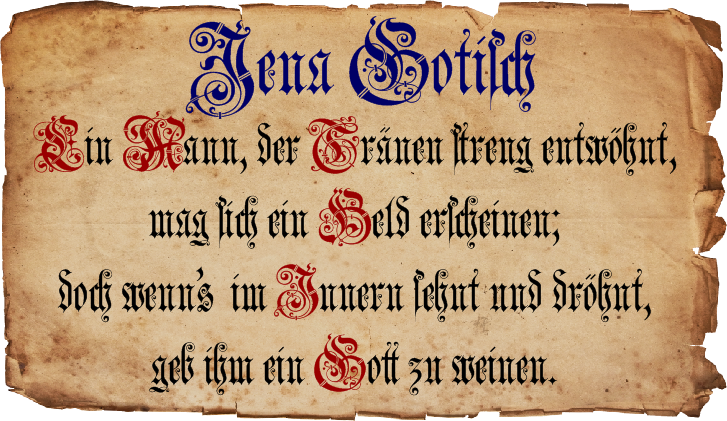
Zierelemente Renaissance
Ich habe mit großer Freude gelesen, dass die EB Garamond auch einen Font mit Initialen besitzt. Bei genauerem Hinsehen stellte sich leider heraus, dass es nur eine Handvoll Buchstaben sind, von denen auch nur zwei (A und T) wirklich gezeichnet sind, die anderen sind abgepaust. Das A gefällt mir allerdings sehr, dummerweise brauche ich ein K.
Ich habe Myfonts nach Alternativen durchsucht und auch die Suchmaschine mit Stichwörtern Renaissance / Initial etc. gefüttert – ohne Erfolg. Entweder passt es stilistisch nicht, oder die Buchstaben sind durch die Illustrator-Autotrace-Funktion gejagt worden und nicht sehr attraktiv. Kennt jemand von euch noch Orte, wo sich eine Suche lohnen würde? So sieht das A der EB Garamond aus:
Dieser Stil würde auch insofern hervorragend passen, da er auf einer Bibelausgabe basiert, die 1564 bei Jean de Tournes in Lyon gedruckt wurde. Das private typografische Experiment, an dem ich gerade arbeite, hat zufälligerweise historische Anleihen bei eben jenem Drucker aus Lyon genommen. Und das bringt mich zu einer zweiten Frage: Tournes Drucke sind mit vielen Zierelementen versehen, die von Bernard Salomon stammen. Eines dieser Elemente würde ich gern benutzen:
Es liegt mir ein Scan in leidlicher Auflösung vor; leider reicht es nicht, diesen als Bild oder als (Autotrace-)Vektor zu verwenden – das Ergebnis sieht nicht besonders gut aus. Man müsste das Ganze wohl sauber neu vektorisieren (und dabei Einzelheiten anpassen). Nun bin ich zwar nicht ganz ahnungslos in Sachen Illustrator-Zeichenwerkzeuge, aber das ist mir dann doch ein bisschen zu kompliziert. Die Frage ist, wer eine solche Vektorisierung übernehmen könnte und was das kosten würde?
Selbst das beste Autotrace ist bei solchen Sachen ja zumeist übelst.
Was die Schnörkelei anbelangt erinnert mich das an die ja auch der nach einem einen Beitrag hier entstandene Schrift:
Zugegeben, das liegt zeitlich deutlich später. Aber wenn es zeitlich Luft hat, und nicht gleich morgen fertig sein muss, beschaff mir doch mal einen Satz ordentlicher (hinreichender) Scans von den Initialen. So was interessiert mich schon sehr, da mal einen ordentlichen Initialen-Satz zu bauen, vielleiche auch noch so ein paar reine Grafikelemente, die ja damals auch gesetzt wurden, passend dazu auf die Gemeinen gelegt.
Danke, catfonts, für die Antwort. Was die Initialen angeht: Eine Ausgabe der besagten Bibel steht bei mir um die Ecke in Gotha, vielleicht kann ich bei Gelegenheit mal vorbeischauen und auf unbürokratische (und preiswerte) Art Fotos machen. Das Problem in Bezug auf mein konkretes Projekt: Die französische Bibelübersetzung hat offenbar kein Kapitel, das mit dem Buchstaben K beginnt (auf den es mir gerade ankommt); für diesen Initialbuchstaben gäbe es also, wenn ich nichts übersehen habe, keine Entsprechung. Aber lohnend scheint mir das Projekt trotzdem: Die Arbeiten von Salomon finde ich wunderschön.
Kein K? ... Nun gut, wenn man sich da eingeschnörkelt hat, muss man halt das K passend erfinden. Das Poblm hatte ich bei der Jena ja auch, das da ein Buchstbe fehlte. Da muss ich dann eben eine zu den Buchstaben in den Schnörkeln passende Schrift finden,m diue dann den Grundbuchstaben dazu spendiert, der dazu dann angepasst werden kann, um dan im gleichen Stil die Vrzieruingen uzu basteln. Wird schon gehen.